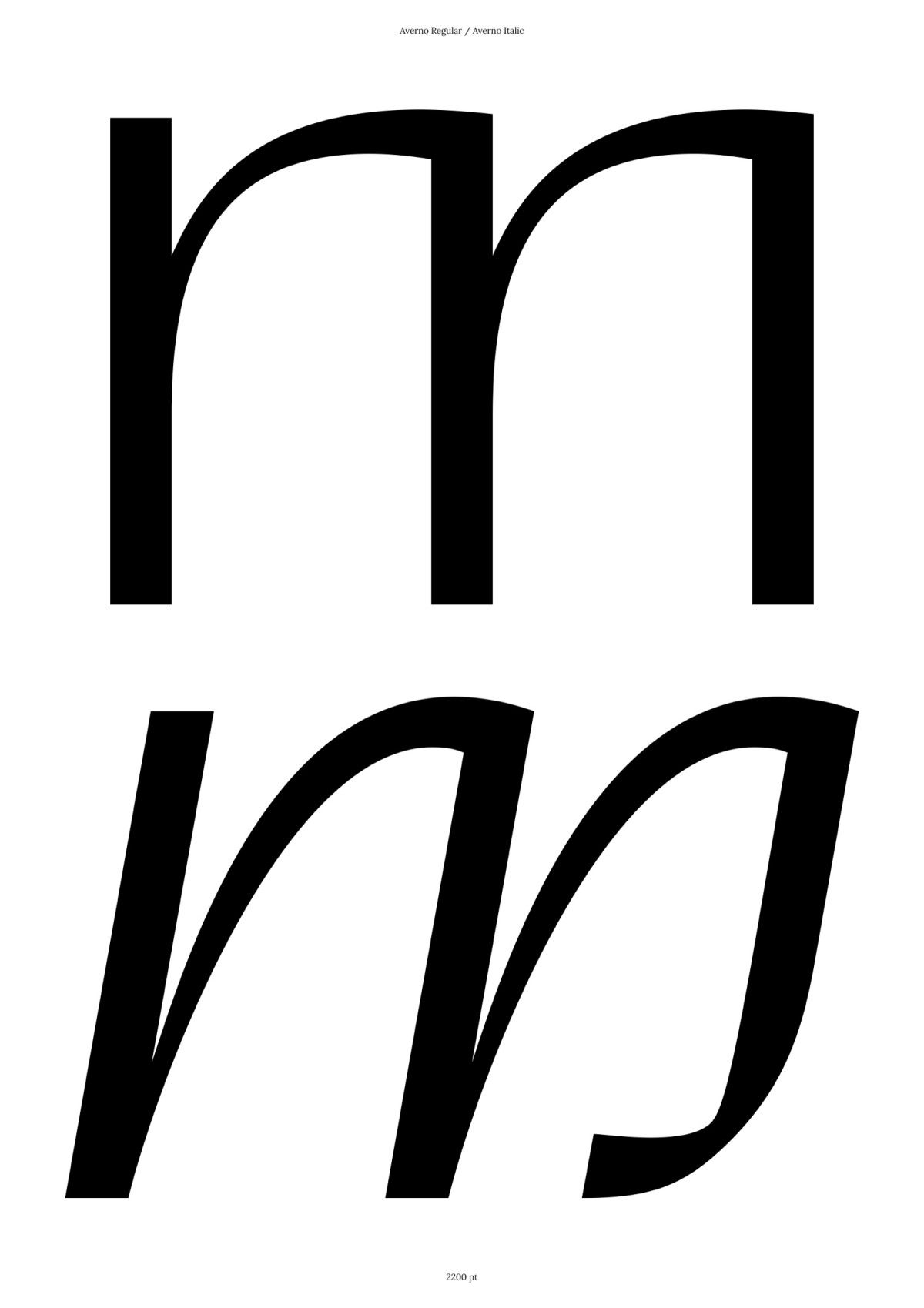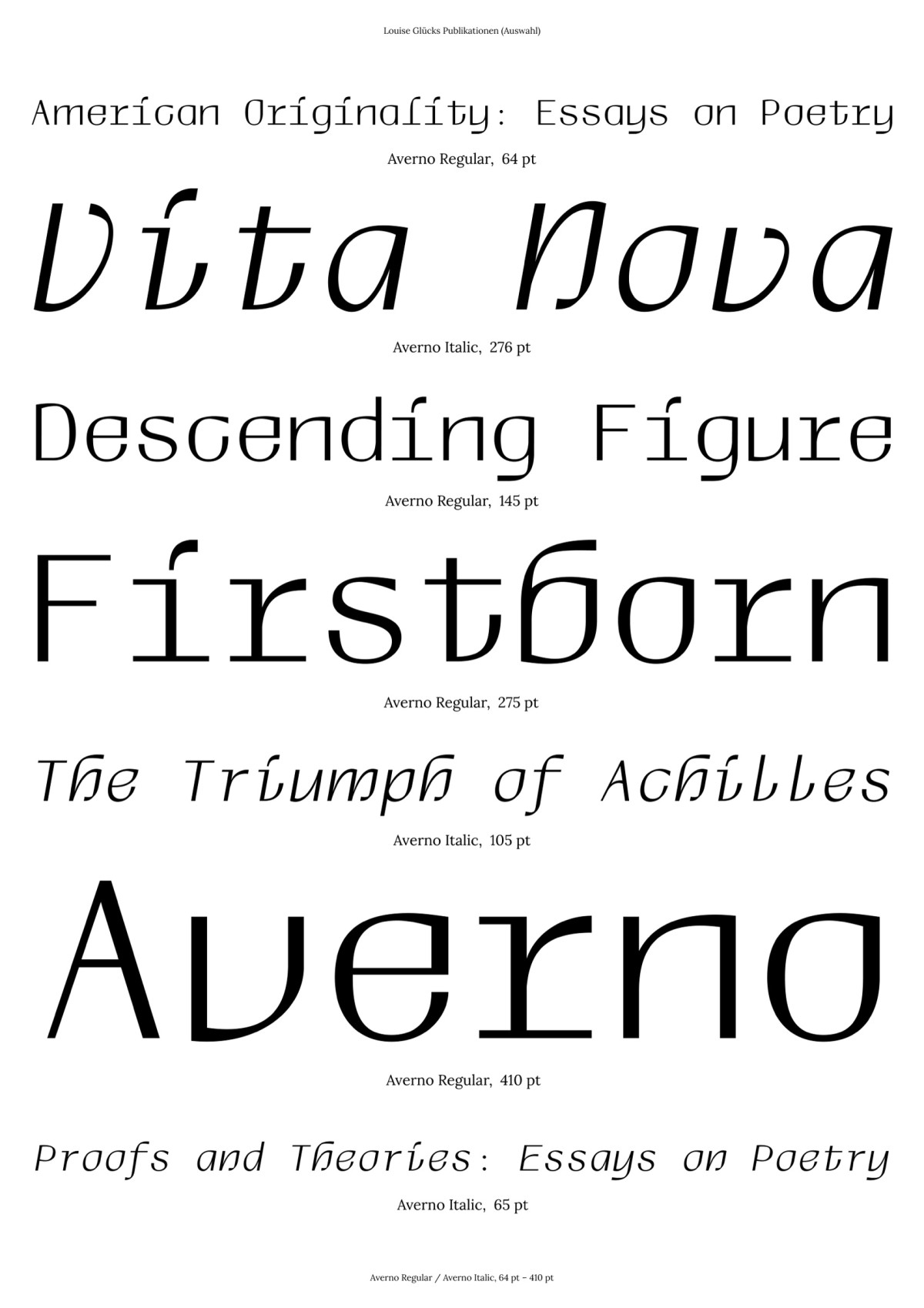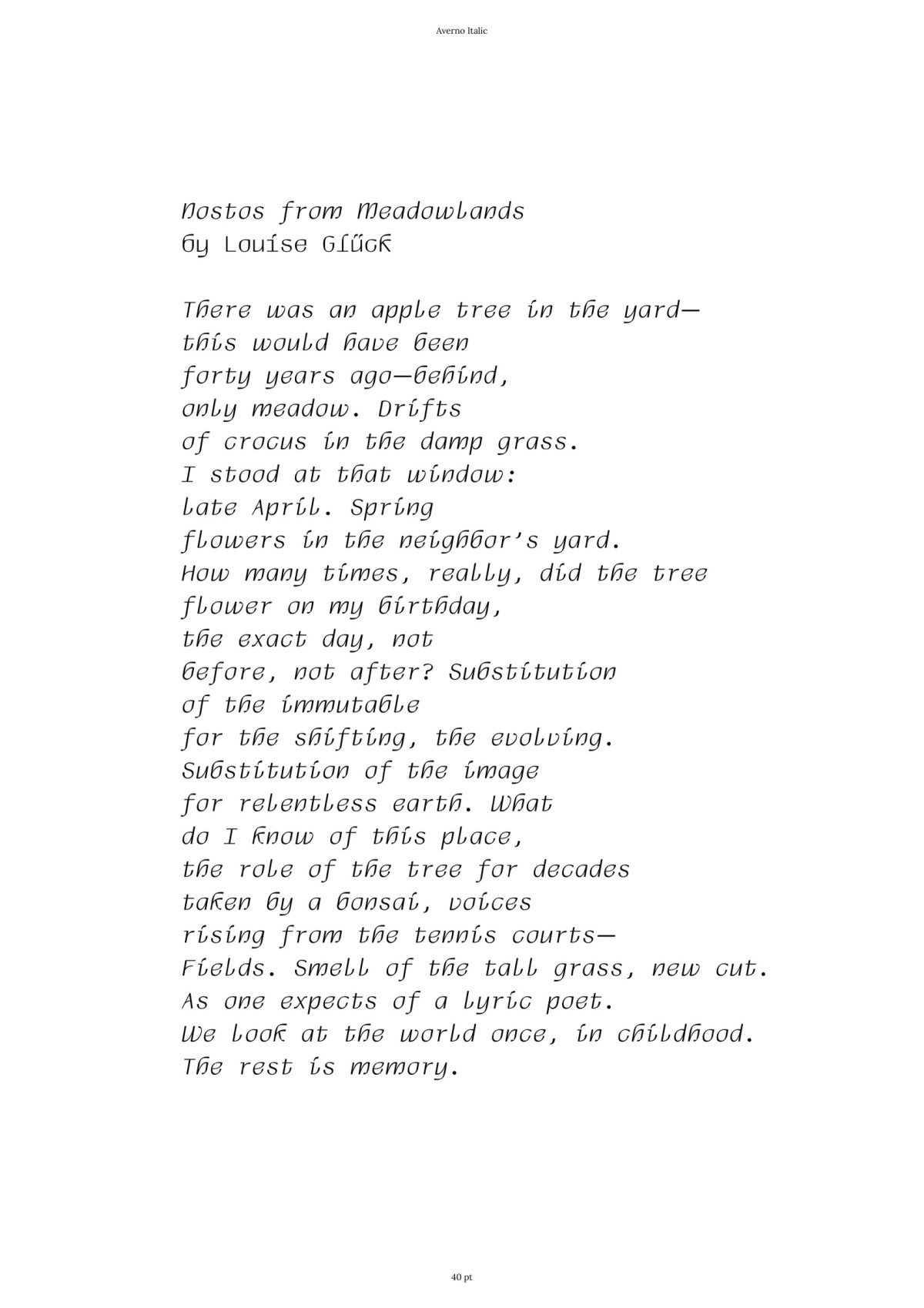
Für mein Bachelorprojekt habe ich die Averno gestaltet – eine Duospace-Schrift inspiriert von der Lyrikerin und Nobelpreisträgerin Louise Glück. Sie besteht aus zwei Schriftschnitten, Regular und Italic, und umfasst etwa 150 Glyphen, darunter Majuskeln, Minuskeln, Ligaturen und Satzzeichen.
Mit ihrer sanften, reduzierten und doch sehr eleganten Sprache schafft Louise Glück Einblicke in den Alltag ganz gewöhnlicher Menschen – Momentaufnahmen aus dem Leben, die ein Gefühl der Nostalgie hinterlassen. Die Averno kombiniert Elemente einer dynamischen und einer statischen Schrift. Hierdurch spiegelt sie Louise Glücks ruhige Ernsthaftigkeit wider und lässt sich in einem literarischen Kontext verorten, behält aber trotzdem eine gewisse Verspieltheit. Die zwei festgelegten Zeichendikten des Duospace-Konzepts verleihen der Schrift den Charakter einer Monospace-Schrift und ermöglichen zugleich den Einsatz von Ligaturen sowie einen ausgeglicheneren Grauwert.
For my bachelor project, I designed Averno – a duospace typeface inspired by the poet and Nobel Prize winner Louise Glück. It consists of two weights, regular and italic, and comprises around 150 glyphs, including majuscules, minuscules, ligatures and punctuation marks.
With her gentle, reduced and yet very elegant language, Louise Glück creates insights into the everyday lives of ordinary people - snapshots of life that leave behind a feeling of nostalgia. Averno combines elements of a dynamic and a static typeface. In this way, it reflects Louise Glück's calm earnestness and can be located in a literary context while still retaining a certain playfulness. The two fixed widths of the duospace concept lend the font the character of a monospace typeface and at the same time allow the use of ligatures and a more balanced grey value.